השאלון עם יובל גרף
הכירו את יובל גרף, ילידת 1999, גדלה בחיפה והיום תמצאו אותה ביפו. יובל היא סטודנטית שנה ד' במחלקה לתקשורת חזותית בבצלאל, וכרגע עובדת על פרויקט הגמר שלה. יובל עוסקת בעיקר במושן גרפיקס, עיצוב גרפי ואיור. ״מאז שאני זוכרת את עצמי, הייתי ילדה של פוסטרים״, היא מספרת, ״אספתי מדבקות, תקליטים ודיסקים (וסליחה אמא על כל מה שקרה לקירות בבית). מבחינתי, כשהעיצוב שלי יוצא החוצה ופוגש את העולם, זה כמו הזמנה לבקר בחדר הפרטי שלי – דבר שהוא תמיד גם מרגש וגם קצת מפחיד״. כשהיא לא בעבודה או בלימודים, יובל אוהבת לצאת החוצה, להסתובב בעיר ולשמוע מוזיקה.
היי יובל, מה שלומך? איפה אנחנו תופסים אותך השבוע?
בתקופה הנוכחית אני מבלה הרבה בדירה שלי ביפו, עובדת על פרויקט הגמר יחד עם חברה מהלימודים. אנחנו יוצרות קליפ אנימטיבי למוזיקאי שאנחנו מאוד אוהבות.
מגניב! את עובדת עכשיו?
כרגע אני בפוּל גז על פרויקט הגמר שלי, אבל כמו שאומרים – open for commission. 😉
את מעדיפה לעבוד לבד או בצוות?
עד לא מזמן עבדתי בעיקר לבד על פרויקטים, אבל השנה גיליתי כמה חזקה יכולה להיות עבודה בצוות. כשיש חיבור טוב נוצר משהו מיוחד שאי אפשר להגיע אליו לבד.
על איזה פרויקט מעניין עבדת לאחרונה?
אחד הפרויקטים המעניינים שיצא לי לעבוד עליהם היה פתיח לסרט פיקטיבי על פי הספר "האמן ומרגריטה" של מיכאיל בולגקוב, יחד עם הדס חיימוביץ׳, חברה מהלימודים (והיום אנחנו גם עובדות יחד על פרויקט הגמר – stay tuned). בפרויקט בנינו עולם שמצד אחד נשען על העלילה, ומצד שני קיבל אינטרפרטציה חזותית מהעולמות שקרובים אלינו במיוחד. חלק משמעותי בפרויקט היה השימוש בטיפוגרפיה כדימוי מרכזי, בהשראת טופסי אשפוז ממחלקות פסיכיאטריות.
מה הדבר הכי טוב שקרה לך השנה?
שיניתי סטטוס ל״תל־אביבית״.
מה גורם לך להתרגש ולרצות לעצב וליצור?
כשאני מוצאת את הקשר ביני לבין הפרויקט – איפה הוא מוצא אותי בחיים האישיים שלי, מה אני יכולה להביא לעיצוב שהוא רק שלי. גם אם זה הדבר הכי רחוק ממני, חשוב לי תמיד לקרב אותו אליי. מן איסטר אגס כאלה שרק אני אבין ואדע על קיומם.
״אלה ניסיונות גרפיים שנוצרו מתוך צורך פשוט ליצור. רובם נעשו באימפרוביזציה, בלי לחשוב יותר מדי על משמעות או מסר – רק מתוך דחף לעצב, להגיב ולשחרר. אני שואבת השראה ממוזיקה (בעיקר אולד־סקול היפ הופ), מתרבות אנדרגראונד ומהאסתטיקה של הרחוב – במיוחד מהפוסטרים האלה שנשכחים על קירות מוזנחים, דהויים, קרועים, אבל עדיין צועקים משהו. מבחינתי, הפוסטר הוא גם פורמט חופשי וגם מרחב אישי להתנסות ולדבר בלי צנזורה.״
מה את עושה כשאין לך מוזה?
יוצאת לצוד פרינט בעיר. חוויית השוטטות והחיפוש מביאה איתה ממצאים מפתיעים שלא הייתי בהכרח מגיעה אליהם דרך חיפוש באינטרנט.
מה את עושה בשביל הכיף?
🙂 .PlayStation and chill
יצא לך לטייל בחו״ל?
בהחלט, אפילו לגור באמסטרדם.
מה משך אותך לתחום?
היה איזה רגע מכונן כשעבדתי כטבחית במסעדה בהולנד, בעלת המקום ידעה שאני מציירת להנאתי והתייעצה איתי לגבי עיצוב לאירוע במסעדה. כשהיא הראתה לי את הסקיצה שלה, הזדעזעתי ואמרתי שזה נראה כמו פוסטר של סופרמרקט. חזרתי הביתה ואמרתי לבת הזוג שלי: נראה לי שאני יודעת מה אני רוצה לעשות בחיים. קיטש, אבל אמיתי לגמרי.
תני לנו ציטוט שיעורר בנו השראה.
Terugkomen is niet hetzelfde als blijven (מהולנדית – לחזור זה נחמד אבל זה לא אומר שתישאר/י).
לאן ניסית להתקבל ללימודים ולאן התקבלת?
בצלאל ושנקר, בחרתי בעיר הקודש.
איזה מרצה השפיע/ה עלייך במיוחד?
רותו מודן ואדם פיינברג.
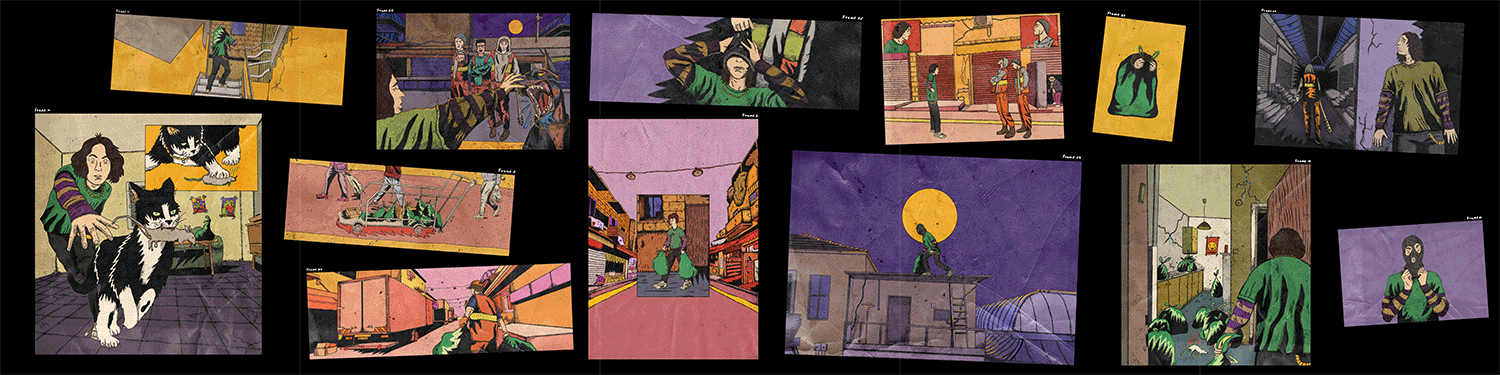
״החיים בזבל״ – קומיקס קצר עם טון הומוריסטי ועוקצני שמספר על החוויה האישית של יובל כדיירת בלב שוק מחנה יהודה בירושלים. הוא מתמקד בניסיונות שלה להיפטר משקית זבל – פעולה שנשמעת יומיומית לגמרי, אבל איכשהו התפתחה למסע סוריאליסטי בין סמטאות, ריבים עם אנשי הזבל ותחושת אובדן שליטה. נעשה במסגרת הקורס ״חייבים לעשות מזה קומיקס!״ בהנחיית רותו מודן.
איזה מעצב/ת השפיע/ה עליך יותר מכל?
הקולקטיב החיפאי Broken Fingaz היו ההשפעה הכי גדולה עליי כבר מגיל צעיר. לכל מקום שהייתי יוצאת בעיר היה חותם שלהם. לפעמים אפילו היינו יוצאים במיוחד עם חברים רק כדי לחפש את הגרפיטי החדש שלהם לפני שכולם מגלים.
במה היית עוסקת אם לא היית מעצבת?
אי־שם בהיסטוריה הייתי בכלל טבחית. כך שאם לא הייתי עוסקת בעיצוב, כנראה שהייתי ממשיכה בעולם המשוגע הזה שנקרא מסעדנות.
איפה את רואה את עצמך בעוד חמש שנים מהיום?
די בטוחה שעדיין מול מסך, מקווה שלפחות המיקום יהיה שווה.
ספר פרוזה/עיון אחרון שקראת.
הקומיקס המצוין Smoking Kills של Thijs Desmet.
רוצה להמליץ על ספר עיצוב?
Karel Martens: Re-printed Matter.
באיזה פונט את רוצה שיכתבו על המצבה שלך?
היציאה הבאה של פונטף, עם איזה גליף של חץ כלפיי מעלה.
יש לך המלצה מוזיקלית?
אני די old fashioned. לאחרונה אני שומעת הרבה את Joey Valence & Brae. יש להם וייב נוסטלגי של היפ הופ ישן עם טוויסט מודרני.
מה משמעות החיים?
טקסטורה.
מה שם החיבה שלך?
מסטיק (סבתלולי הייתה דבוקה אליי).
קיצור מקלדת אהוב.
4 + ⇧ + ⌘ (צילום מסך ב־mac).
כתבי בבקשה את המילה הבאה בכתב היד שלך: